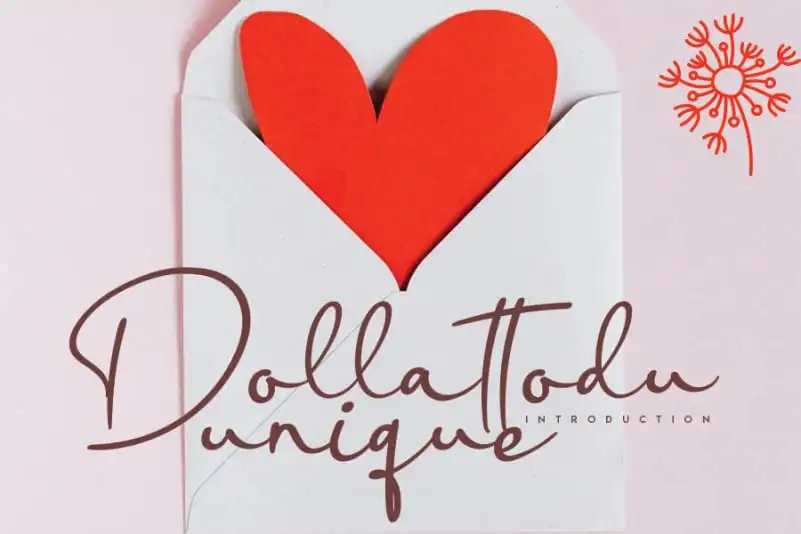
Dollattodu Handwritten Font – Download Grátis
Dollattodu Handwritten Font é uma criação única que surge do incrível encontro entre a caneta-pen e o lápis, dando ao resultado uma aparência encantadora e autêntica. Este belo tipo de escrita à mão traz um toque especial e único para qualquer projeto DIY. Com seu design natural e fluido, Dollattodu Handwritten Font é perfeito para decorar suas criações digitais ou físicas. Seja você criando uma instalação interativa, adesivos personalizados ou até mesmo um novo logotipo, essa fonte vai dar aos seus projetos um toque delicado e autêntico.